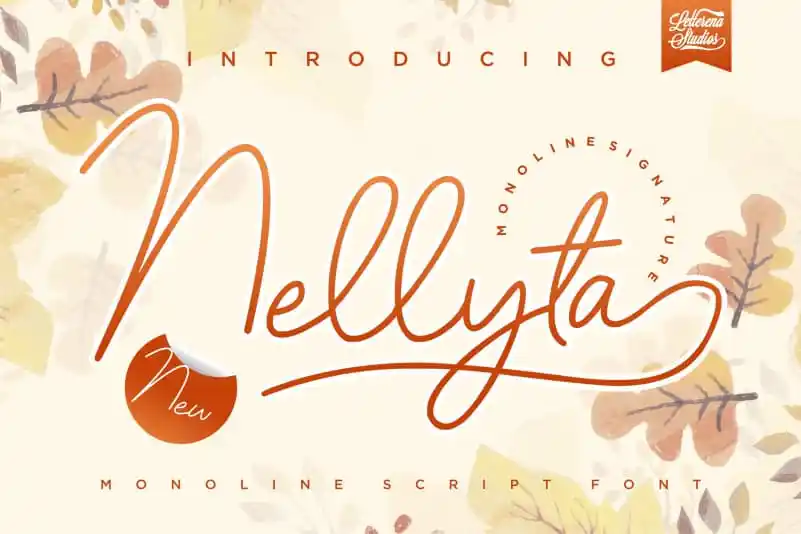
Nellyta Monoline Font – Fonte Grátis
Nellyta Monoline Font
A Nellyta Monoline Font é uma elegante escolha para quem busca personalidade no design de letras. Suas linhas retas e finas proporcionam uma sensação moderna, ideal para criar assinaturas distintivas e ricos elementos gráficos. Inspirada pela letra manuscrita, a fonte apresenta um ar sofisticado que combina harmoniosamente com diversas aplicações visuais. Com o formato “Signature Fonts”, esta fonte é perfeita para quem busca uma solução sólida e duradoura para criações de assinaturas e logotipos. O designer, letterenastudios, entrega um trabalho cuidadoso que valoriza a autenticidade da escrita manuscrita, resultando em linhas levemente onduladas que adicionam uma pequena textura, mantendo o equilíbrio entre simplicidade e estilo. Personal Use Only (Uso Só Pessoal) é um claro indicativo de respeito aos direitos autorais. Seja você criador ou usuário casual, este termo garante que a fonte seja usada apenas por intenção pessoal e não em contextos comerciais sem autorização adicional. Essa preocupação com os direitos autorais destaca a responsabilidade ética do designer letterenastudios.